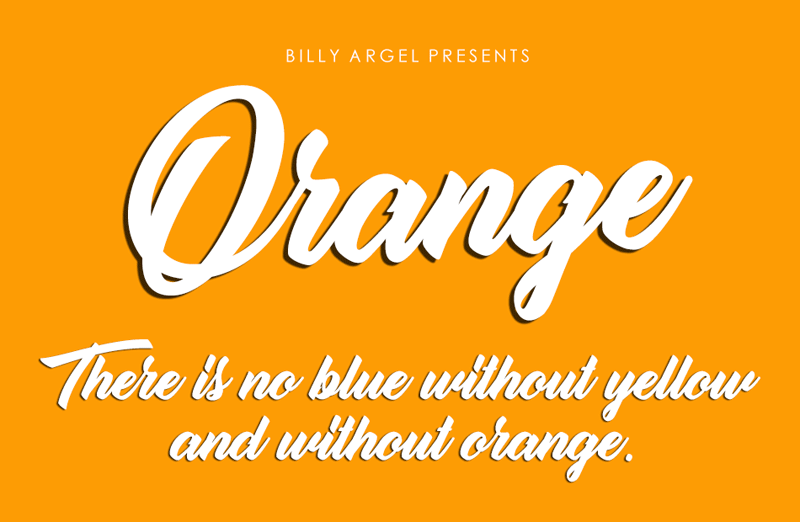
Aqui está uma descrição em português para a página de download da fonte ‘Orange Script Font’: Na categoria de Script Fonts, você encontrará a autêntica e encantadora Orange Script Font, projetada pelo talentoso designer Billy Argel. Esta fonte é perfeita para aqueles que procuram uma maneira criativa de adicionar um toque elegante aos seus materiais digitais. Com seu estilo fluido e versátil, a Orange Script Font permite criar mensagens memoráveis em sua página de blog, projeto de site ou até mesmo no design de produtos pessoais. Designada para se adaptar perfeitamente tanto ao uso pessoal quanto à necessidade de licenciamentos comerciais, a fonte oferece uma experiência intuitiva e de alta qualidade. Se você está à procura de uma fonte que traga um toque autêntico às suas criações digitais, não procure mais além da Orange Script Font. Para obter mais informações ou para acessar o catálogo completo de licenciamentos, confira a página oficial do designer, disponível em www.billyargel.com. Garanta a sua versão personalizada e experimente o prazer de criar design com uma fonte tão única e sofisticada quanto a Orange Script Font.
Designer: Billy Argel